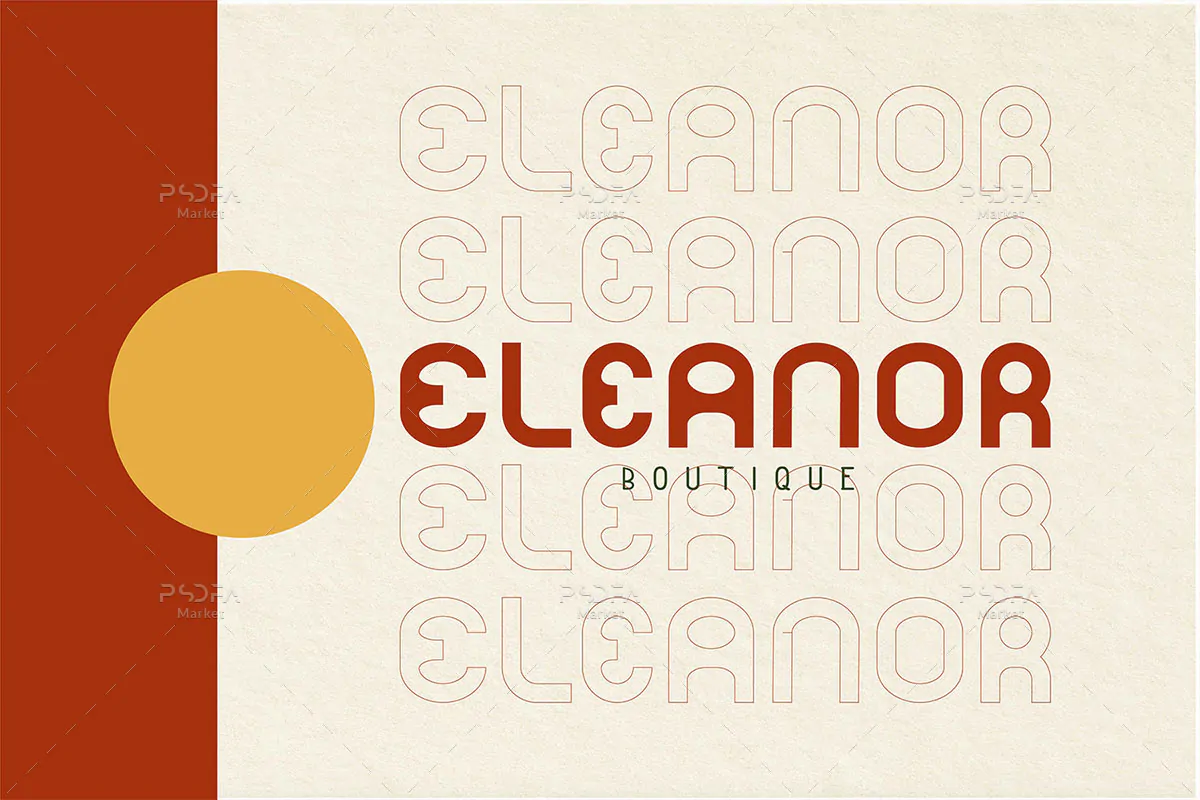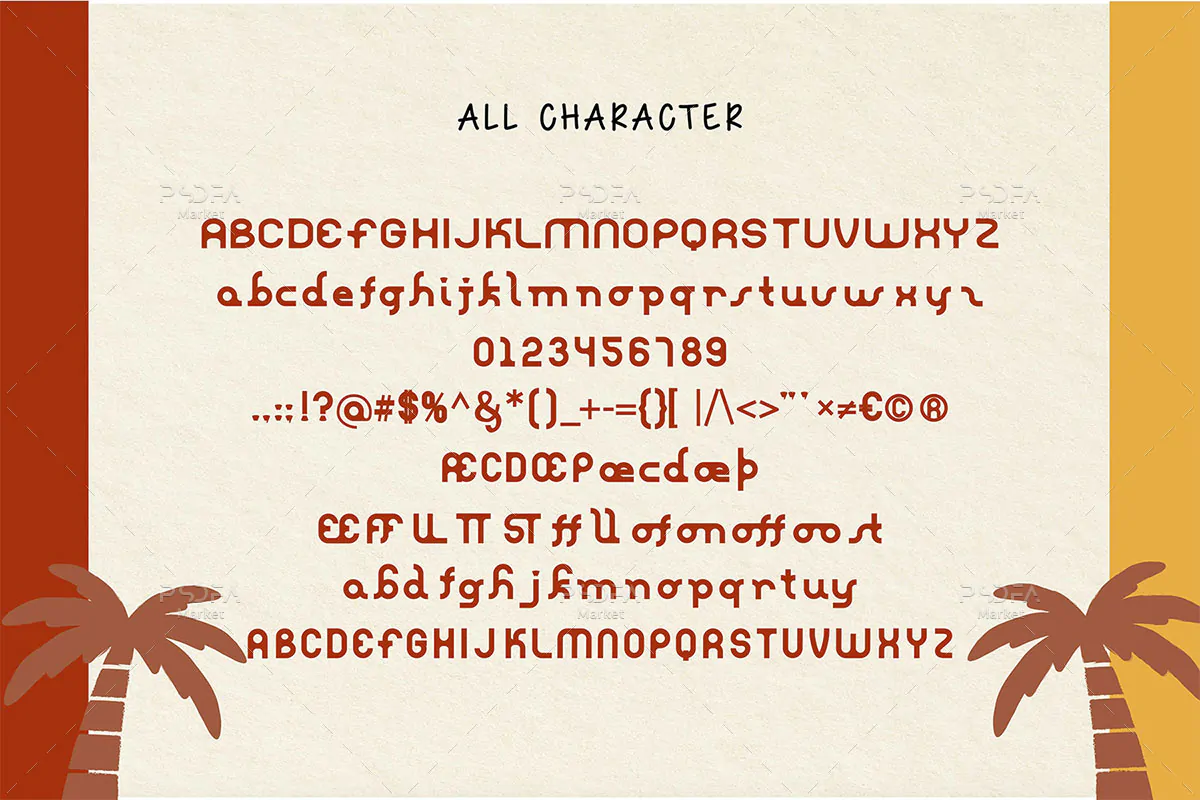
فونت یونیک و منحصر به فرد Circool
فونت یونیک و منحصر به فرد
فونت یونیک و منحصر به فرد Circool یک قلم نمایشی فوق العاده زیبا است که مناسب جهت استفاده در طرح و پروژههای گرافیکی مختلف میباشد. فونت Circool با وزن معمولی طراحی شده است که میتوانید از آن در طراحی پوستر، کارت ویزیت، بروشور، مجلات، کتب، لوازم التحریر، ظروف یکبار مصرف، بسته بندی محصولات، لوگو، تیشرت و … استفاده کنید.